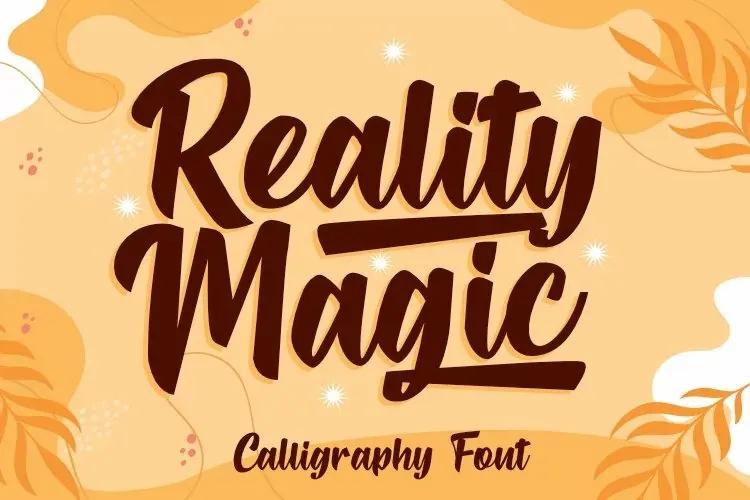
Reality Magic Font
A Fonte Reality Magic é uma elegante tipografia serifada criada pelo Eknoji, perfeita para quem busca uma fórmica minimalista e sofisticada. Esta fonte atinge um equilíbrio entre modernidade e luxúria, proporcionando resultados incríveis tanto em gráficos digitais quanto impressos. Seu design de letra chamativa é o produto de anos de experiência e criatividade do designer Eknoji. Ideal para uma ampla gama de aplicabilidades, a Fonte Reality Magic pode ser utilizada em logos, embalagens de produtos, convites de casamento, identidades visuais, subtítulos, selos, assinaturas, capas de livros, panfletos e até mesmo em citações. Suas formas fluidas e levemente esculpidas são perfeitas para um trabalho que exige uma mistura de elegância e sofisticação. Através desta fonte, você pode criar designs impressionantes com um toque único. Ela não apenas oferece um nível excepcional de detalhe e qualidade, mas também transmite uma sensação de luxo que faz a diferença em qualquer projeto. O design delicado e os traços delicadamente realçados proporcionam resultados profissionais e elegantes, tornando-se uma opção ideal para aqueles buscam estilizar suas criações de um modo singularmente sofisticado. Para quem busca tanto um estilo moderno quanto uma aparência luxosa em seus designs, a Fonte Reality Magic é uma escolha perfeita. Seja você um designer gráfico, um editor de fotos ou mesmo um criador de conteúdo pessoal, esta fonte oferece a capacidade de criar designes memoráveis e sofisticados que destaquem seu trabalho.